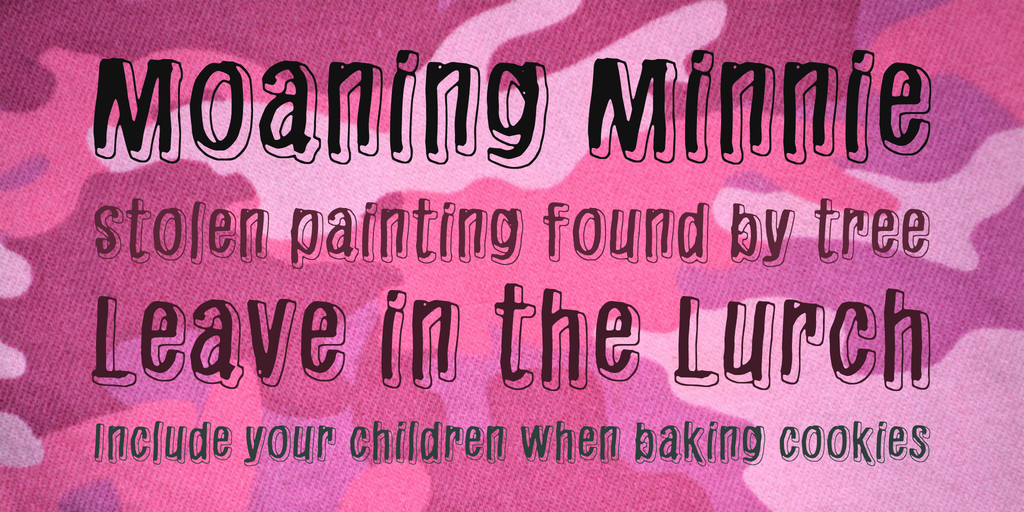
Aqui está uma descrição em português do Brasil para a página de download da font ‘Redhair Font Made’, focada em tornar a experiência envolvente e natural: Estamos muito felizes por você encontrar esta bela fonte que combina elegância com personalidade. A fonte “Redhair Font Made” criada pelo designer Hamilton é gratuita para uso pessoal, mas se deseja usá-la em um projeto comercial, é necessário adquirir a licença comercial, que custa 15€ ou $20 através do PayPal. Não hesite em entrar em contato com Hamilton para obter as informações mais detalhadas sobre o pagamento e os procedimentos para obtenção da licença. Após fazer seu depósito, você pode enviar uma mensagem de email para Hamilton confirmar a compra e receber a sua chave de acesso à fonte. A fim de apoiar nosso desenvolvedor Hamilton, que investiu tempo e energia nesta bela criação visual, também podemos oferecer a opção de doações. As contribuições regulares são muito bem-vindas e ajudam Hamilton a continuar criando mais belas e únicas fontes para o seu catálogo. Nossa fonte “Redhair Font Made” é perfeita para projetos que desejam destacar-se com um design único, tornando sua identidade visual ainda mais forte. Para descobrir mais sobre como você pode incorporar esta fonte em seus projetos de design gráfico, visite nossa página dedicada a recursos de fontes.